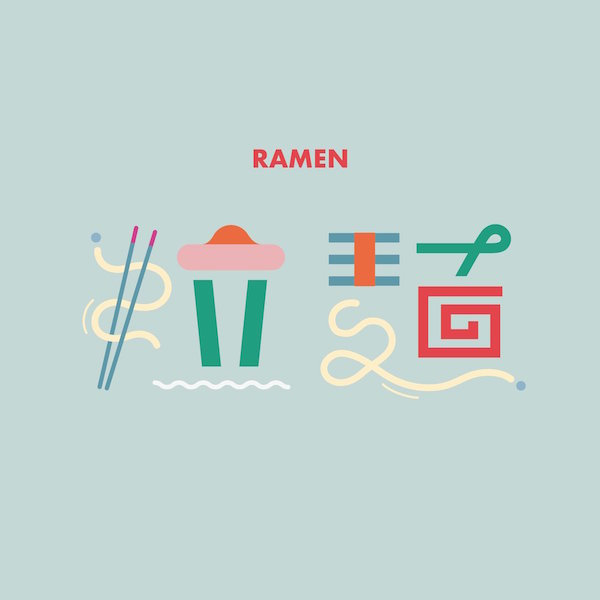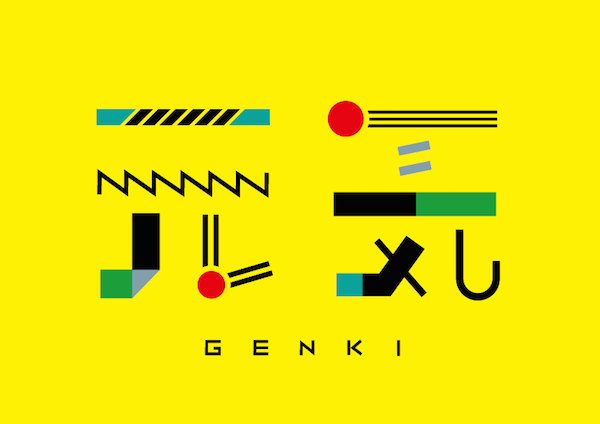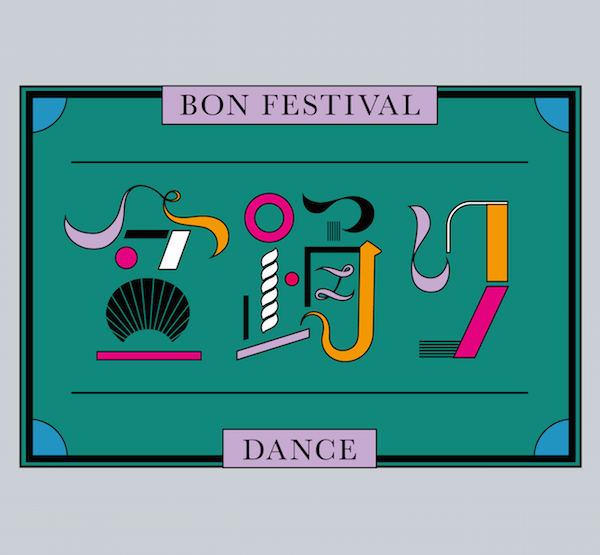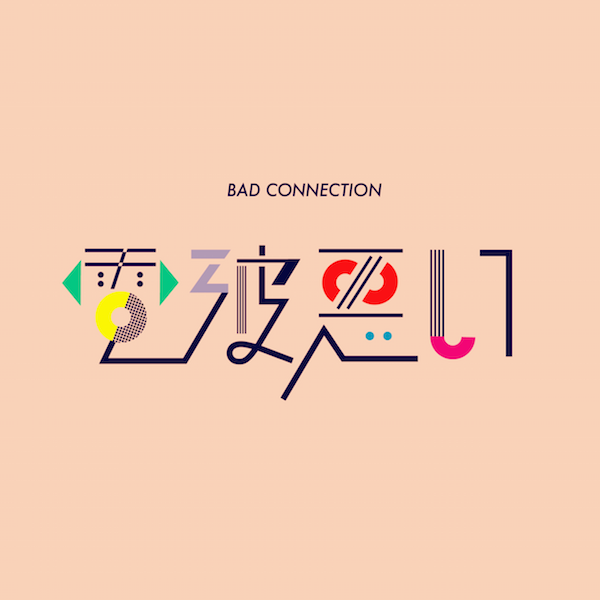
Nozaki Azusa es un diseñador y tipógrafo que ha realizado una experimento bastante interesante basado en la tipografía japonesa de forma ilustrativa.
En pocas palabras, el trabajo de Azusa consiste en utilizar palabras en el idioma japones para ilustrarlas usando tipografía; tal es ejemplo de la palabra Ramen, el cual, dentro de su diseño experimental contiene algunos fideos dentro su cuerpo originalmente escrito: ? ?.
Sabiendo esto, aquí te dejamos unas imágenes del trabajo de Nozaki Azusa; misma que desgraciadamente no puede ser descargada al ser un proyecto experimental e ilustrativo.